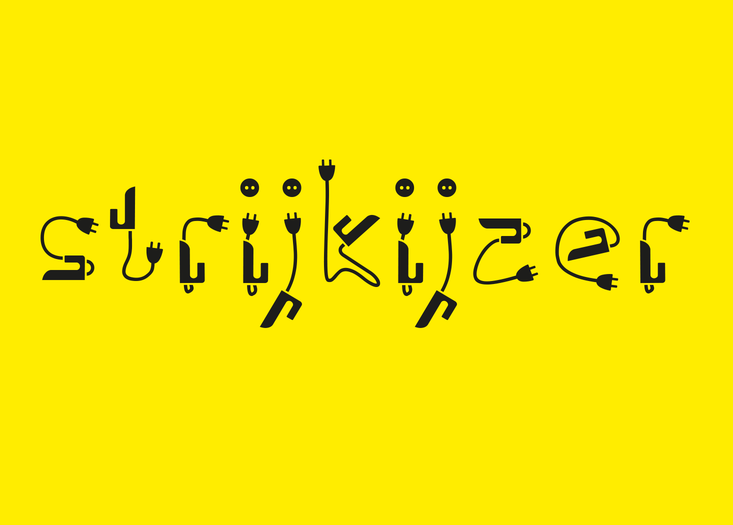
Esta página oferece uma breve descrição do ‘Ps Strijkijzer Font’, uma fonte de símbolos criada pelo designer Hamilton. Originalmente projetada como uma brincadeira entre amigos, esta fonte foi posteriormente elevada ao status de fonte premium. Atualmente, está disponível gratuitamente para download no MyFonts. O nome ‘Strijkijzer’ é uma referência a ferramenta de escrita tradicional e evoca um sentimento jovial e irreverente. Afinal, esta não é uma fonte séria, mas sim um acerto entre amigos que agora pode ser experimentado sem custo algum. Se você gosta de um toque leve e divertido nas suas criações digitais, ‘Ps Strijkijzer Font’ será definitivamente o tipo certo para você.